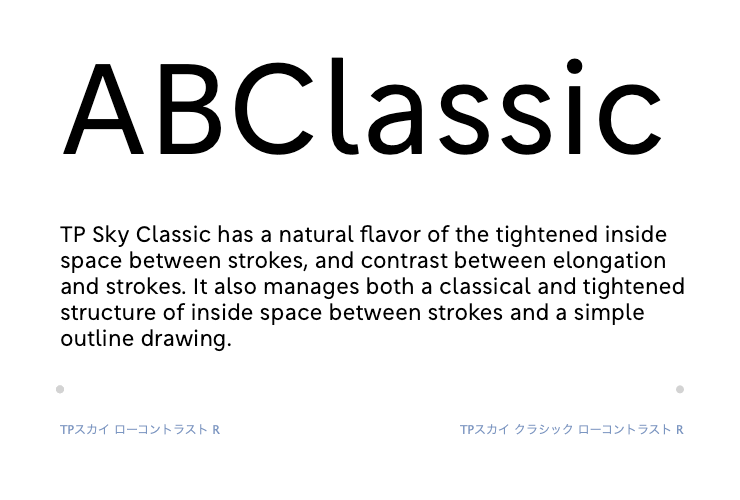
TPスカイ クラシック欧文開発ストーリー02「TPスカイ ベーシックとの比較」
TPスカイの欧文は比較的均一な字幅を持っています。一方でTPスカイ クラシックは古典的な骨格をベースとして持っているため、字幅の差があります。Bなどは引き締まり、Cなどは空間を大きくもったデザインになっています。また、小文字のx-heightを低くすることで和文のフトコロを引き締めるのと同様の効果でクラシックな雰囲気を出しています。単語で見ても変化はありますが、文章を組んだ時もまた、引き締まりながらも落ちつきを持ちます。